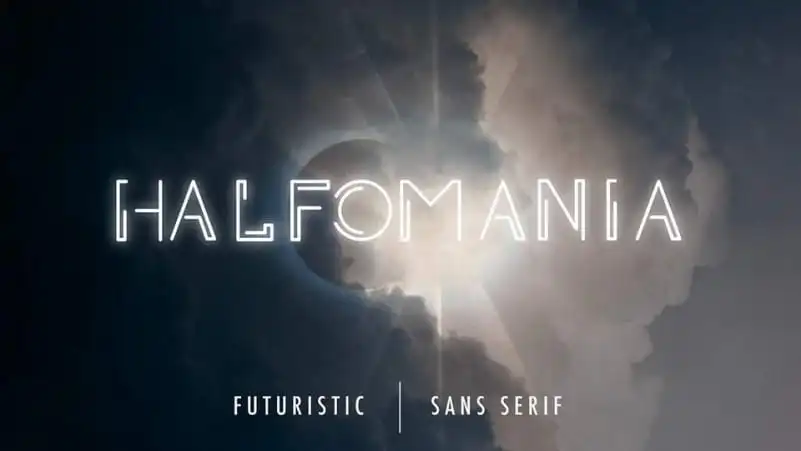
Halfomania Display Font – Download Grátis
A Halfomania Display Font é uma tipografia minimalista e futurista projetada pelo designer Azer Nesib para o site 99designs. Esta tipografia moderna apresenta um ar clássico ao misturar formas geométricas minimalistas com elementos de letra moderna, oferecendo um visual único perfeito para headlines ou design de marca. Com uma combinação de letras maiúsculas e minúsculas, números e símbolos inclusos na mesma fonte, ela é ideal para várias aplicações, incluindo posters, logotipos, revistas e muito mais. Sua simplicidade a torna perfeita para criar designs frescos e modernos sem comprometer a legibilidade. Para aqueles procurando por uma combinação única de clareza e modernidade, a Halfomania Display Font é um excelente adicional ao seu arsenal de fontes.